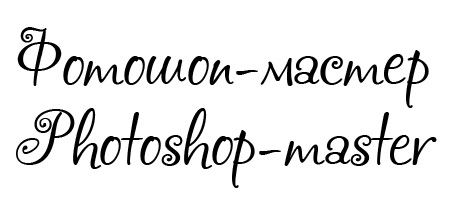
Спасибо, отличный шрифт, красивый и читабельный!
Очень удобный шрифт для навигационного меню сайта))) Спасибо большое Photoshop-master))
Креативно :) Мне нравится. Я качаю для оформления форума, думаю, мне подойдет. :)
Красивый шрифт, русский, сейчас опробовал в Paint.
отличный шрифт для журнала подходит!именно то что я искал!
Отличный шрифт как раз для сайта искал
симпатичный!!
Очень красивый шрифт!